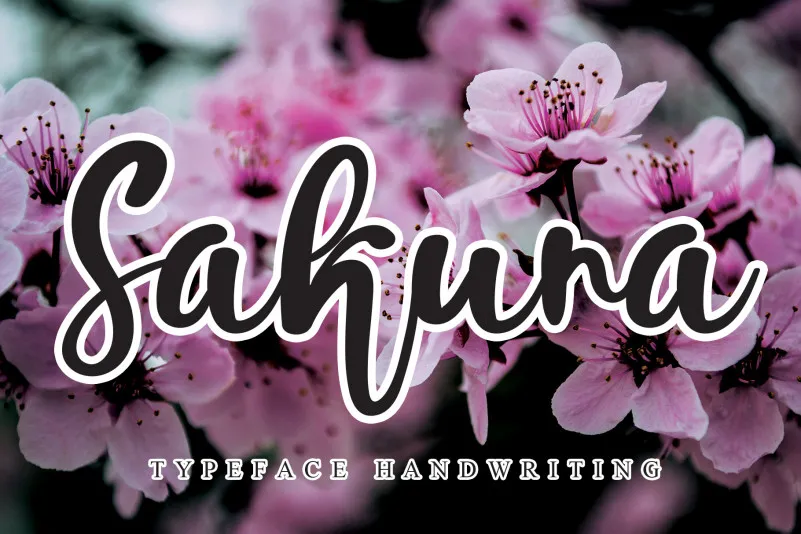
Sakura Script Font – Download Grátis
Sakura Script Font é uma fonte script escrita a mão que transmite uma sensação encantadora e eterna. Embora seja perfeitamente adequada para criar logomarcas memoráveis, identidades de marca e citações interessantes, ela também oferece um toque único e belo em cada letra. Seja você criando materiais visuais exuberantes ou simplesmente adorning textos com uma leveza e elegância, Sakura Script vai transformar seus designs em algo que se destaca da multidão. Esta fonte foi projetada pelo designer andikastudio para a categoria de handwrited fonts, garantindo que cada letra possa ser uma pequena obra-prima, enriquecendo seu trabalho com uma autenticidade e originalidade genuínas.